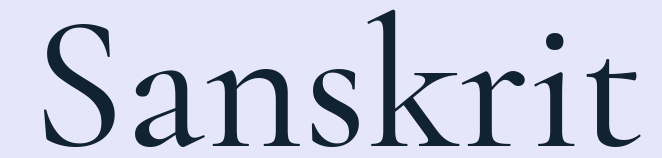
Font mit Diacritica für geisteswissenschaftliche Arbeit
ich bin auf der Suche nach einem geeigneten Font, der Sanskrit-Diakritika gut darstellt und Serifen hat. Ich bin jetzt über den Adobe Devanagari reg. gestolpert, der dies auf den ersten Eindruck schön bewältigt. Wenn der Kommentar (irgendwo im Netz) stimmt, ist der Font Deckungsgleich mit dem Minion. Wichtig für den Font ist vor allem die Verwendung bei einem Buchdruck.
Bislang hatte ich einen Font namens "The Brill" verwendet, den ich aber nicht zum Druck hernehmen kann, da Brill ein Verlagshaus ist und ich wohl bei einem anderen publizieren werde.
Hier eine Auswahl der Diakritika: ĀāīūśṣṭṢŚñḥṃṇṛḍ
Viele der modernen Fonts stellen sie dar, aber häufig mit Unregelmässigkeiten.
Wenn der Kommentar (irgendwo im Netz) stimmt ...
Wenn man Deine Auswahlzeichen auf dieser Seite eingibt
sieht man in der Tat, dass es sich um die Minion handelt. Die "normale" Minion-Version kann diese Zeichen nicht (jedenfalls erinnere ich mich daran, mal einen Artikel gesetzt zu haben, in dem ich die entsprechenden Sonderzeichen selbst aus der Minion "basteln" musste). Wenn es nicht allzu viele Stellen sind, an denen diese Zeichen benötigt werden, ist "Basteln" also auch eine Alternative (wenn auch nur im Sinne eines Notbehelfs).
Falls du freie Schriften durchsuchen möchtest, kuck mal hier: http://type.dt1.org/render/all?tag=serif&has=ṃ&text=ĀāīūśṣṭṢŚñḥṃṇṛḍ. Da sind auch ein paar gute Schriften dabei, die sich durchaus für anspruchsvolle Druckaufgaben eignen, darunter die (explizit für vielsprachige Publikationen geschaffenen) SIL-Schriften sowie die Garamond-inspirierten Cormorant und EB Garamond.
(Der Neigungswinkel der Ś- und ś-Akuts lässt sich per SS13 und Spracheinstellung Polnisch angleichen. Leider kann das Schriftmuster das hier nicht wiedergeben, aber du kannst das bei Bedarf hier testen.)
Laut Font Infos deckt die Schrift auch alle gebräuchlichen westeuropäischen Sprachen ab, wahrscheinlich ist das alles, was Du benötigst. (Aber wie gesagt, zu den besten Kaufoptionen bräuchten wir mehr Infos.)
P.S.: Die von Thorsten verlinkte Gentium hat übrigens der Brill-Verlag für viele (zeichentechnisch anspruchsvolle) Publikationen verwendet, bevor er sich seine eigene Hausschrift hat gestalten lassen.
Ich tendiere jetzt auch wegen der Einfachheit (ein Font, keine Tweaks notwendig) zur Adobe Devanagari.
Die Gentium Plus habe ich jetzt auch mal installiert und die schaut auch recht gut aus. Bietet die Devanagari nun einen Vorteil über die Gentium? Wie vorher schon erwähnt, ist vor allem das gedruckte Bild wichtig. Ich arbeite mit Word, wenn das in Bezug auf die Fonts überhaupt eine Rolle spielt.